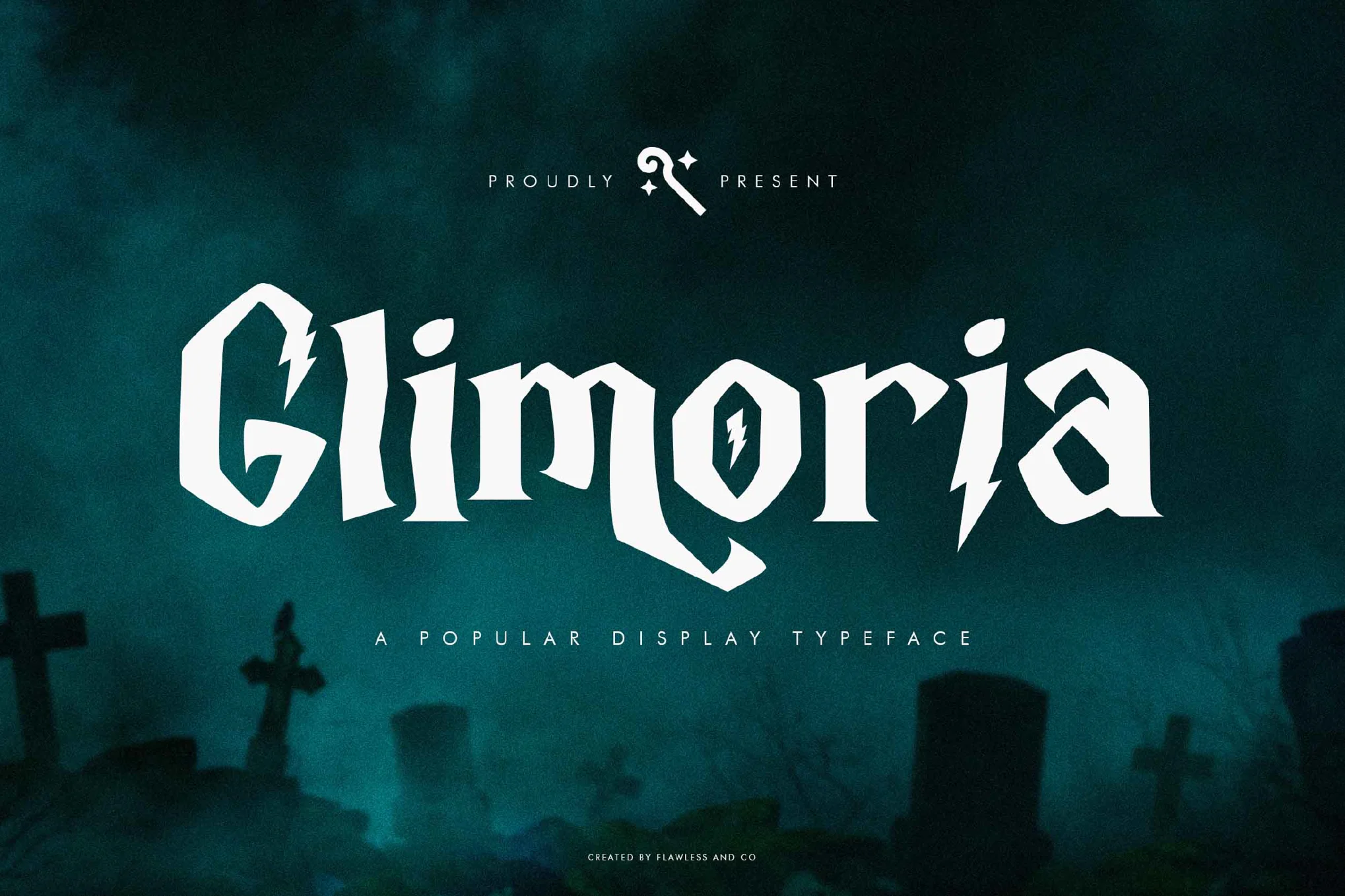
دانلود فونت Glimoria – Horror Font
Glimoria یک فونت نمایش ترسناک است که حال و هوای ترسناک و ترسناکی را به طرح های شما می بخشد. این فونت با لبههای تیز و زیباییشناختی شگفتانگیز خود، برای پوسترهای فیلمهای ترسناک، طرحهای با مضمون هالووین، دعوتنامههای شبحآمیز، جلد کتابهای هیجانانگیز، عناوین بازی، و پروژههای نام تجاری وهمآور مناسب است. ظاهر ناراحت کننده و در عین حال فریبنده آن فوراً فضای تاریک عالی را ایجاد می کند.